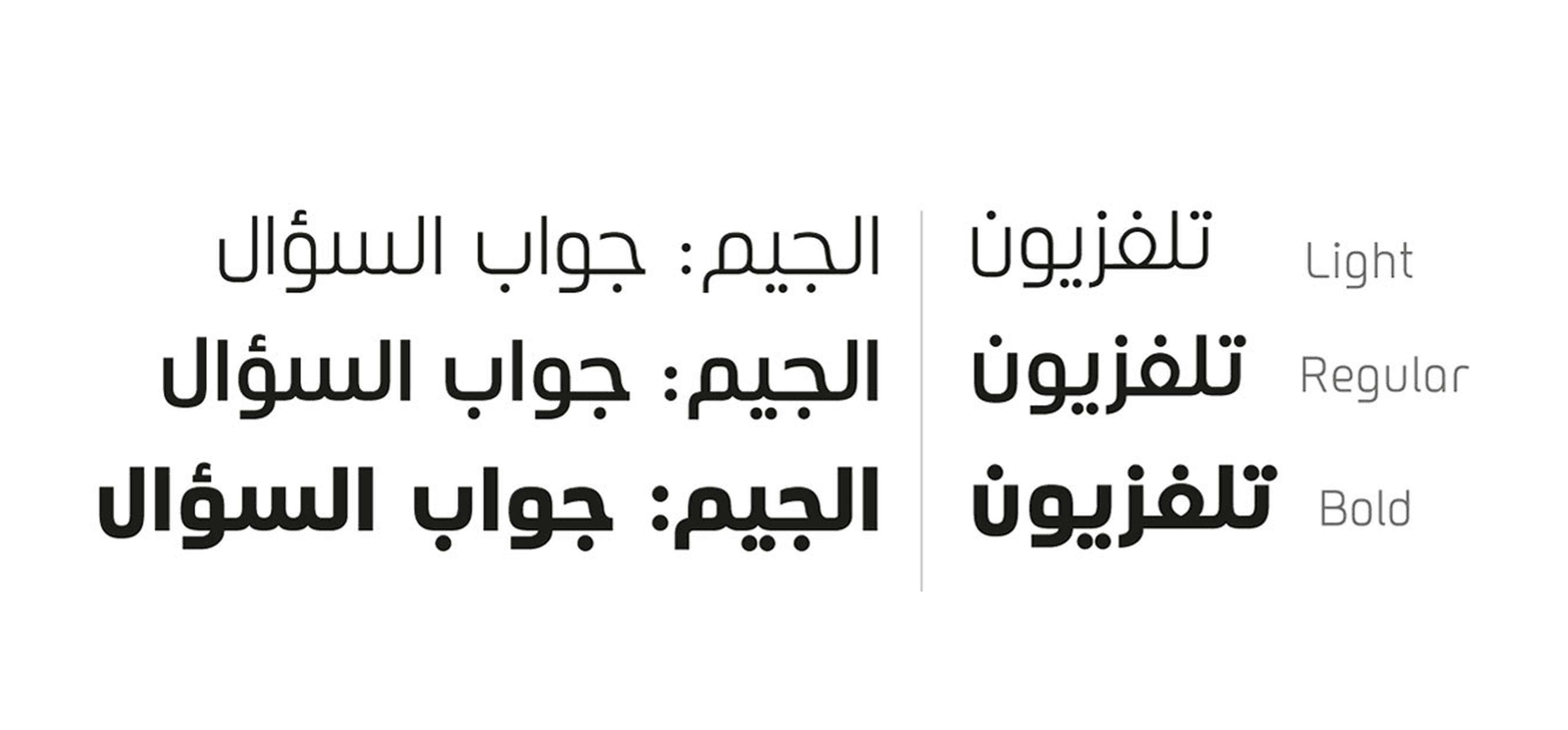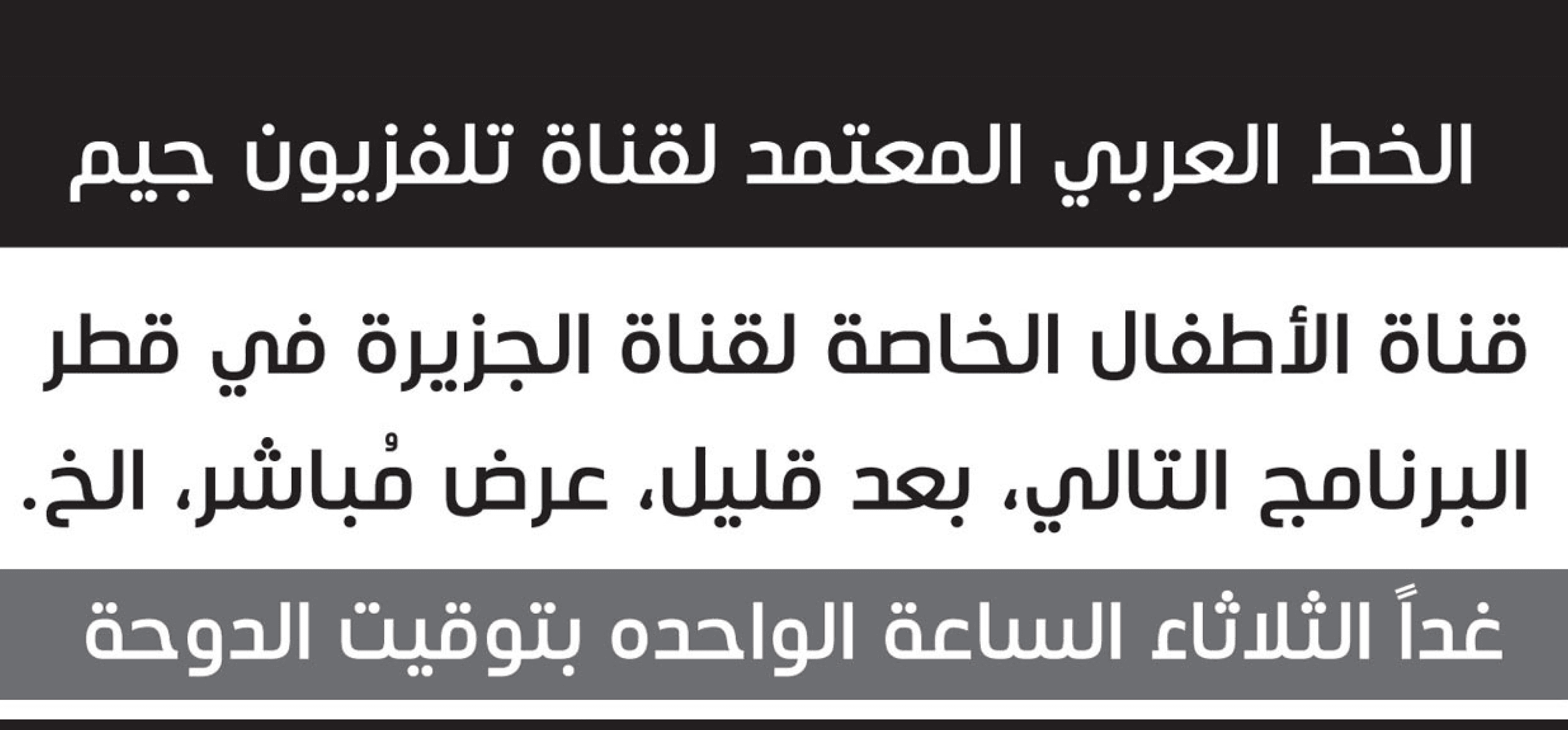
تُعد قناة جيم التلفزيونية القناة العربية الرائدة في مجال تلفزيون الأطفال، وتعمل تحت مظلة شبكة الجزيرة الإعلامية، أكبر شبكة إخبارية في العالم العربي ومقرها في قطر.
كانت تُعرف سابقًا باسم قناة الجزيرة للأطفال (JCC)، وقد أعادت القناة إطلاق هويتها بالكامل في عام 2013 لتظهر بشكل جديد يعكس أهدافها واستراتيجيتها الجديدة (يمكنكم قراءة المزيد عن مشروع الهوية على صفحتنا الخاصة بالعلامة التجارية). وقد تم تكليفنا في Arabictypography.com بتصميم خط مخصص ثنائي اللغة (عربي ولاتيني) لاستخدام حصري من قبل القناة.